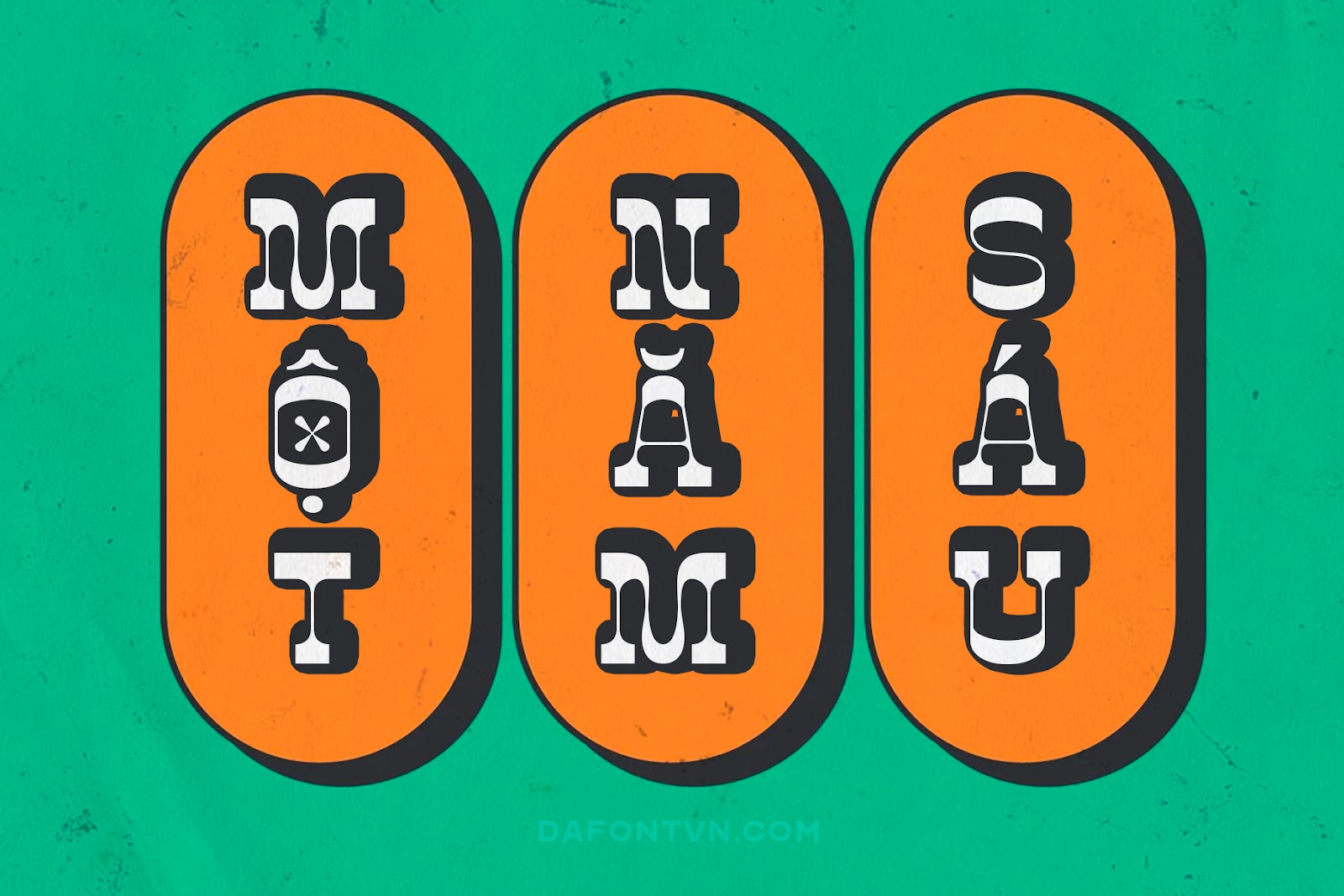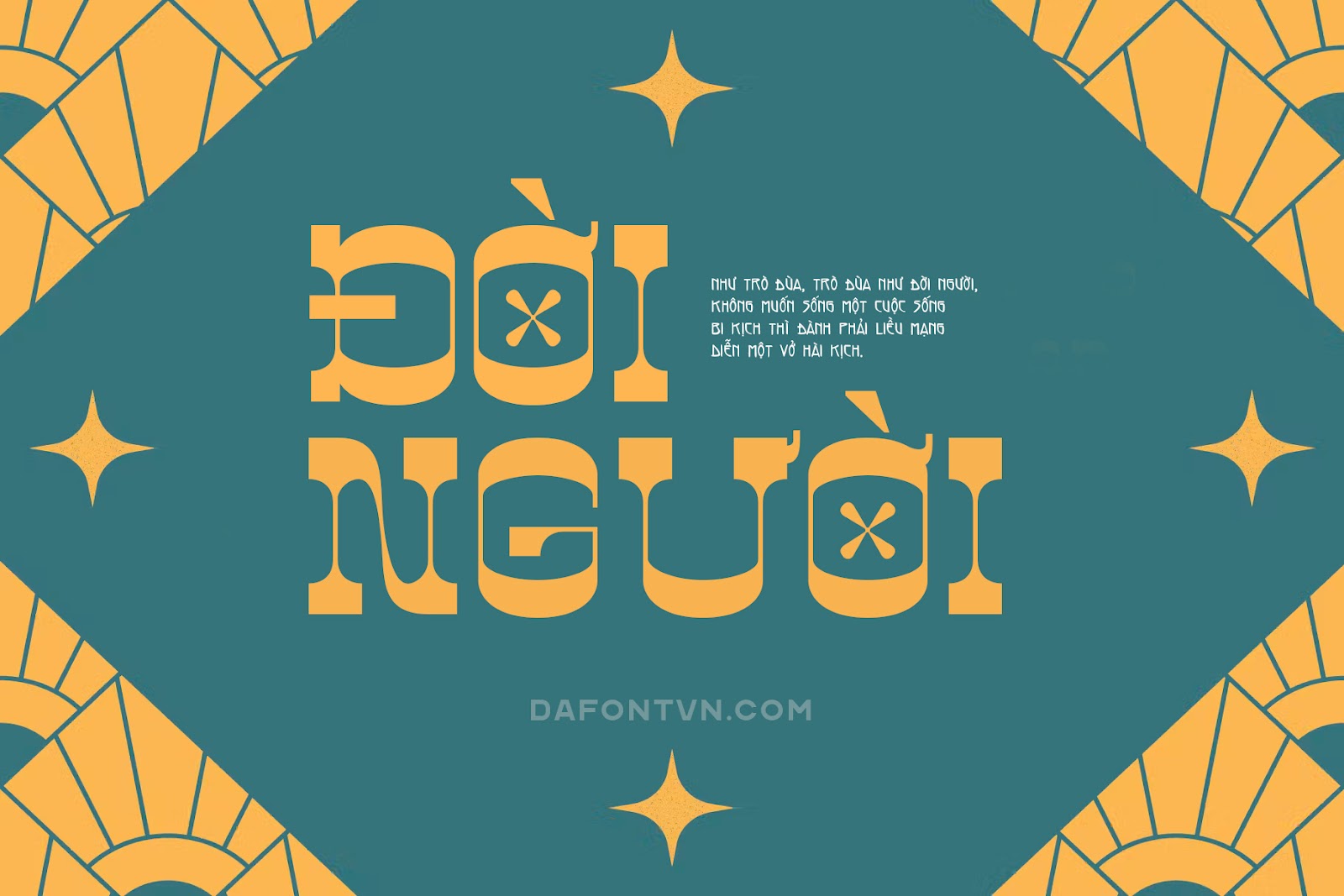
Font Việt Hóa Reboy – Display Typeface
Reboy – Display Typeface được lấy cảm hứng từ các sản phẩm văn hóa như văn hóa âm nhạc, nghệ thuật, văn học, thời trang và phim ảnh trong những năm 1980. Font khá phù hợp cho các thiết kế như logo, tiêu đề.